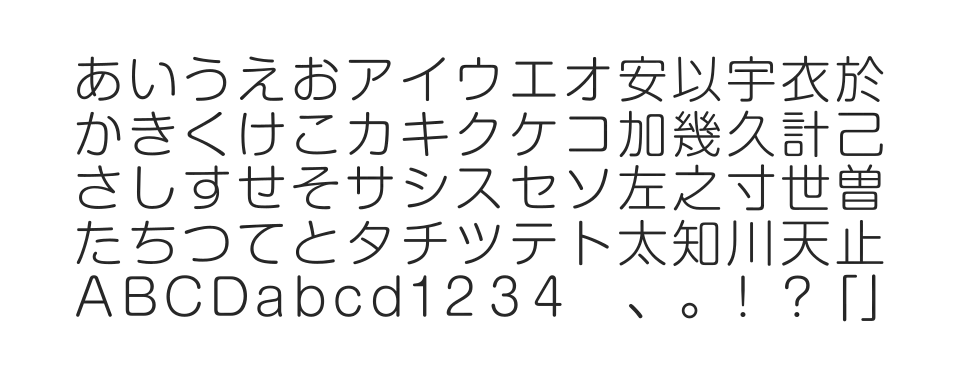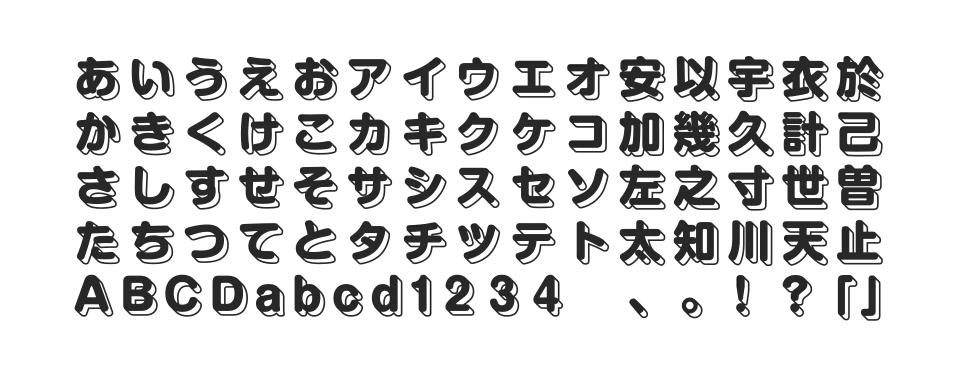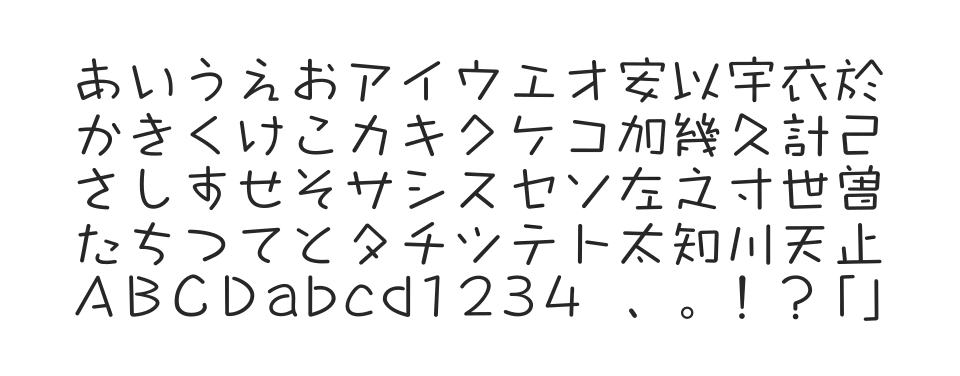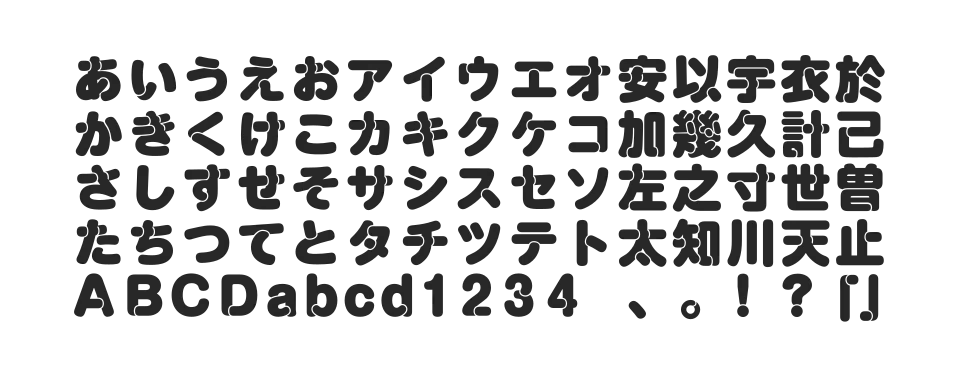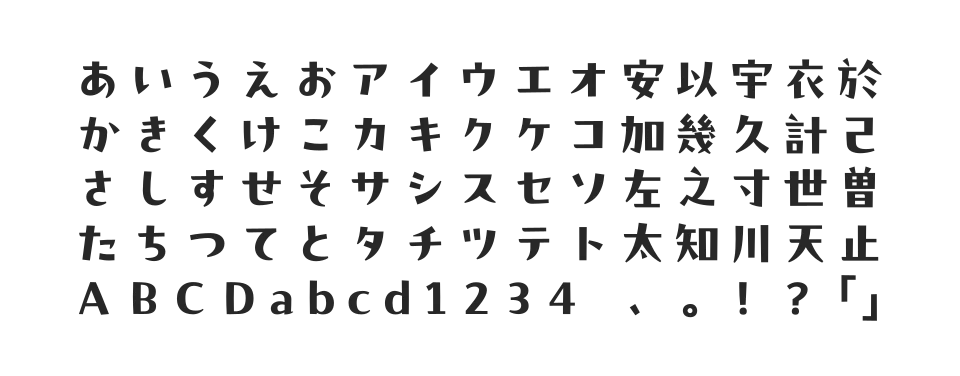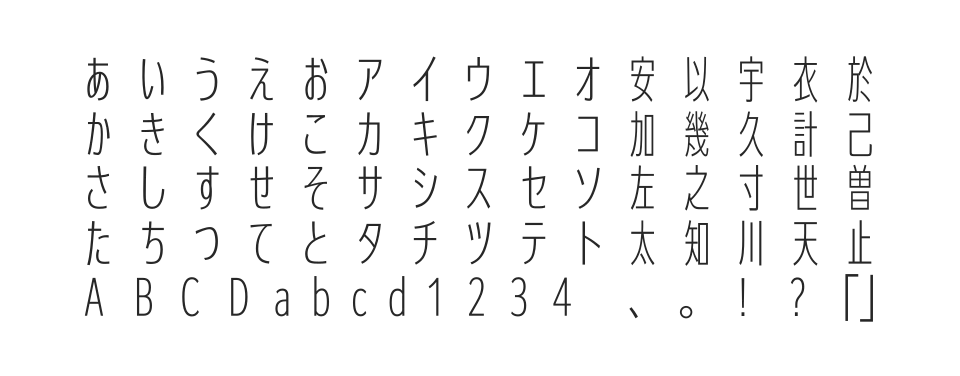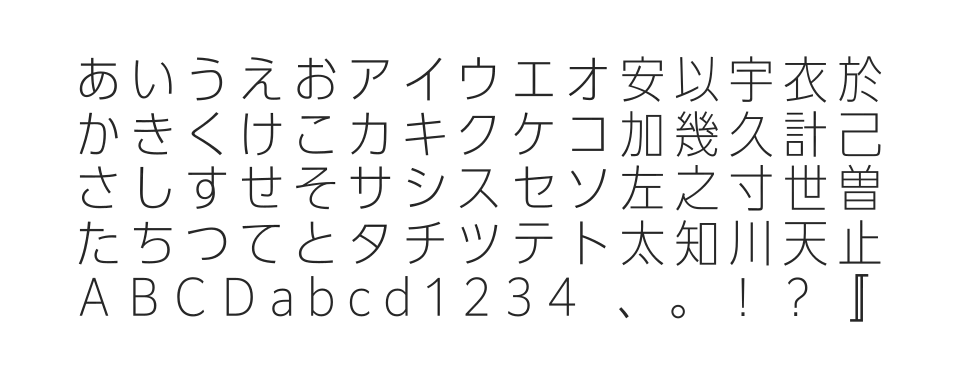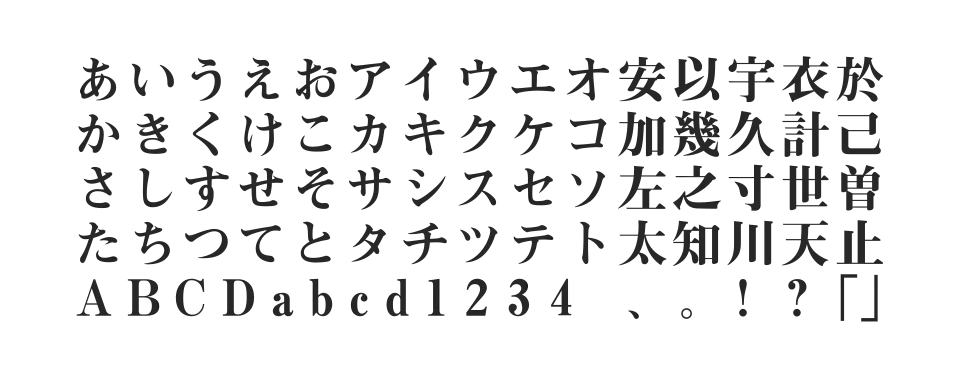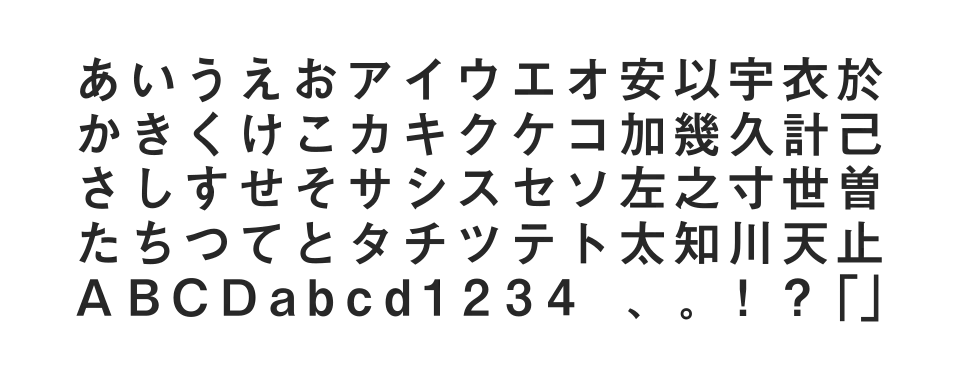
太ゴB101と見出ゴMB31の中間に位置する伝統的なゴシック体。始筆にアクセントをもったオーソドックスなデザインで、漢字と仮名の黒みのバランスが整えられ、読みやすさを重視して設計されている。
重厚さと風格を備えた伝統的な見出明朝体。確かな太みと存在感をもつ漢字に対してかなはやや細めに設計されており、漢字とかなの対比によって可読性の高さを引き出している。モリサワ基本7書体の一つ。
UD新ゴをベースに展開したコンデンス(長体)書体。長体率90%で、食品の成分表示やパッケージの注意書き、チラシ、書籍の帯、Webのバナーなど様々な用途で活用できる。高いデザイン性も兼ね備えている。
UD新ゴをベースに展開したコンデンス(長体)書体。長体率50%で、限られたスペースでも可読性を保ちながらより多くの情報を表示できる。縦画と横画の太さや骨格のバランスが最適化されている。
プフシリーズの一つで、すっきりとしたハライを持つハイコントラストなデザインが特徴。統一しすぎない自由な字形と小さめの字面で、パッケージや書籍の装丁などで個性的な表現を実現。
画線と画線の重なりがくいこんだような立体的なデザインが特徴の丸ゴシック系書体。極太の丸ゴシック体が持つ愛らしさと独特の立体感があいまって、人の目を引きつける力強さを表現。
勢いのあるかな文字と、のびやかな漢字で構成された手書き風デザイン書体。画線同士をあえて触れ合わないようにすることで愛らしい印象を生み出し、点画のバランスをあえて崩すことで語りかけるような表情を表現。
システマチックな雰囲気をもつ現代的なゴシック体。装飾のない均質で明るいデザインで、スマートで洗練されたイメージ。あらゆるグラフィックデザインや広告に最適です。
モダンなゴシック体として人気の高い「新ゴ」をもとに誕生した丸ゴシック体。明るく洗練された雰囲気に加えて、丸味のあるエッジがもたらすやさしいイメージと親しみやすさが特徴です。